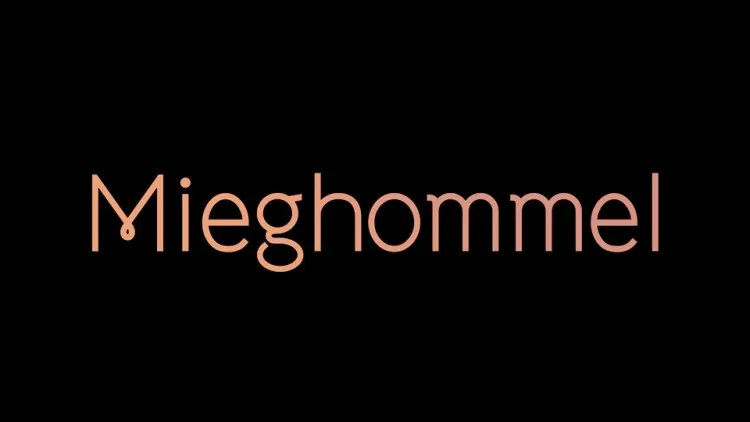
A Mieghommel Font é uma elegante escolha para projetos digitais que exigem simplicidade e modernidade. Ela foi criada pelo designer de fontes Tup Wanders e é uma variedade simples e minimalista do tipo de sans-serif, com curvas suaves na extremidade dos caracteres. Esta fonte é perfeita para uso em cartões de visita, cartazes promocionais, anúncios e até mesmo em notas pessoais ou outros tipos divertidos de projetos digitais. Suas linhas retas combinadas com as curvas delicadas trazem uma sensação contemporânea que se adapta perfeitamente para estilos tanto formais quanto informais, tornando-a um recurso gráfico valioso no seu arsenal de fontes.